Веб-шрифты и веб-безопасные шрифты – это два разных понятия, связанных с использованием шрифтов на веб-сайтах. Прежде чем мы начнем, давайте немного проясним терминологию.
В чем разница между шрифтами .
- Веб-безопасные шрифты: также известные как «системные шрифты» или «браузерные шрифты», веб-безопасные шрифты – это шрифты, установленные на всех устройствах и браузерах.
- Веб-шрифты: хотя и нечеткие, веб-шрифты относятся ко всем шрифтам, которые не являются веб- безопасными шрифтами, особенно к коммерческим и независимо разработанным шрифтам.
Таким образом, веб-безопасные шрифты являются наиболее распространенными, доступными в Windows или Mac, Chrome или Safari. Таким образом, веб-шрифты не так легко доступны, и обычно вам приходится загружать и устанавливать их сами.
Какой из них использовать в веб-дизайне?
У них обоих есть свои преимущества и недостатки.
Для веб-дизайна, который является средой, рассматриваемой в этой статье, главное преимущество веб-безопасных шрифтов заключается в том, что они загружаются быстрее, что сокращает время, необходимое для загрузки вашего сайта. Это не большая разница, но если вы хотите сократить каждую потерянную миллисекунду, они имеют значение.
Обратной стороной веб-безопасных шрифтов является то, что они универсальны. В них нет ничего уникального или оригинального – они доступны буквально каждому. Если вам нужен стиль или артистизм, вам придется использовать другой веб-шрифт.
Веб-шрифты отличаются гораздо большим разнообразием; это набор шрифтов, которые постоянно добавляются и расширяются. Вы можете получить лучшие веб-шрифты для своего бренда, специально разработанные на основе того, что вы ищете, или вы можете лицензировать уже существующий онлайн из концентратора шрифтов. Главное их достоинство – это, конечно же, оригинальность. Если вам нужен выделяющийся шрифт, веб-безопасные шрифты его не подберут.
Если у вас возникли проблемы с принятием решения, воспользуйтесь этой полезной блок-схемой от Дэвида Гилбертсона из Hackernoon (имейте в виду, что он использует «системные шрифты» для обозначения «веб-безопасные шрифты»).
А как насчет индивидуальной эстетики шрифта?
Но выбор между лучшими веб-шрифтами и лучшими веб-шрифтами – не единственное ваше решение. Вы также должны решить, какой стиль типографики подойдет вашему бренду и функциям сайта. Различные шрифты лучше подходят для длинных блоков текста, чем для привлекающих внимание заголовков, не говоря уже о том, как они влияют на восприятие вашего бренда.
В этом руководстве мы разбиваем их все на три категории, основанные на эстетике шрифта: с засечками, без засечек и декоративные. Для тех, кто не знает, засечки – это те маленькие метки или «флажки», которые иногда появляются на концах букв. Мы объясним рекомендуемое использование каждого из них ниже, а также то, как они отражаются на идентичности вашего бренда.
Когда использовать веб-шрифты с засечками в веб-дизайне
Засечки имеют долгую историю в типографике. Но если вы ищете шрифты для веб-сайтов, все, что вам нужно знать, это то, что засечки относятся к «серьезной» стороне спектра. Это делает их отличными для профессиональных и официальных брендов, но немного противоречивыми для дружелюбных и повседневных брендов, если они не настроены соответствующим образом.
Ищете ли вы лучший веб-шрифт или веб-шрифт, засечки лучше всего подходят для брендов, которые хотят передать авторитет, изысканность и класс. У них классическая привлекательность из истории, поэтому они хорошо работают с брендами, которые существуют в течение долгого времени, или брендами, которые хотят так выглядеть . Компромисс заключается в том, что шрифты с засечками могут восприниматься как серьезные, возможно, излишне формальные, поэтому, если вы используете их, они должны работать с ценностями вашего бренда, чтобы не оттолкнуть целевую аудиторию.
Также стоит отметить, что шрифты с засечками удобны для чтения, поэтому их часто используют для основного текста, заголовков и подзаголовков. Это не значит, что шрифты без засечек плохо читаются; они отлично подходят для длинных блоков текста. Но есть причина, по которой высококлассные издания, такие как The New York Times и Boston Globe, до сих пор используют веб-шрифты с засечками для своих цифровых статей. И, не случайно, обе эти газеты склоняются к «формальному» и «классическому» стилям брендинга, продвигая при этом длинный текст.
Размер и стиль шрифтов также имеют решающее значение. Крупные и яркие засечки сделают ваш шрифт более стилизованным, а в крайних случаях – более ярким и профессиональным. Точно так же более мелкие и крошечные засечки менее формальны – идеально, если вы ищете золотую середину между «серьезным» и «забавным».
Лучшие веб-шрифты с засечками:
Когда использовать без засечек веб-шрифты?
Шрифты без засечек – полная противоположность шрифтам с засечками как по форме, так и по тому, как они воспринимаются зрителем. В этом случае sans буквально означает «без засечек», поэтому все шрифты без засечек – это шрифты без засечек.
Как вы понимаете, шрифты без засечек более просты и беззаботны. Они не выглядят так, как шрифты с засечками. Sans serifs – это шрифты для дружеской беседы и неформальных сообщений, напоминающие простой почерк. Они разработаны для скорости и простоты, возможно, за счет приличия.
Шрифты без засечек лучше всего подходят для веб-сайтов, которые хотят показать своим посетителям: «Мы такие же, как вы». Они непринужденные и непринужденные, идеально подходят для учебных материалов, цифровых публикаций или блогов. Если вы много шутите или используете смайлики в своих статьях, шрифт без засечек теоретически подойдет лучше всего.
По этой же причине веб-шрифты без засечек являются предпочтительным выбором для неформального и дополнительного текста: подписей к изображениям, публикаций в социальных сетях, подписей, заявлений об отказе от ответственности и веб-рекламы. Шрифты без засечек лучше работают в тексте, когда чтение выполняется быстро и без срочности, поэтому важно понимать, как ваша целевая аудитория потребляет тип контента, который вы хотите создать, прежде чем выбирать, может ли это быть лучшим веб-шрифтом (или безопасным для Интернета). font) для вас.
Лучшие веб – шрифты без засечек:
Лучшие веб-шрифты без засечек:
Когда использовать декоративные веб-шрифты.
Наконец, у нас есть декоративные шрифты, которые могут быть шрифтами с засечками или без засечек. Они также могут быть лучшим веб-шрифтом или веб-безопасным шрифтом для ваших заголовков и заголовков. Декоративные гарнитуры имеют богатый дизайн; они должны быть художественными или стилистическими, с большим упором на то, как они выглядят, чем на то, что они говорят. Хотя большая часть типографики предназначена для функциональности, эти шрифты предназначены для зрелища.
Декоративные шрифты лучше всего подходят для выделения и акцента, например заголовков, выделенных цитат или заголовков статей. Они – вишенка на торте, поэтому используйте их экономно и для драматического эффекта. Они добавляют индивидуальности, юмора и креативности, только не переусердствуйте. Думайте об этом как о добавлении соли в готовку и избегайте подавления вкуса аудитории. Это означает, что они не будут работать для длинных блоков текста или подписей к изображениям. Ни для контактной информации вашего бренда, ни для текста в вашем нижнем колонтитуле.
Поскольку декоративные веб-шрифты подходят для всех стилей и индивидуальностей, они могут отлично работать в сочетании с более простыми шрифтами с засечками или без засечек. Но никогда не жертвуйте удобочитаемостью ради внешнего вида. Декоративные шрифты – это только развлечение, пока читатель не сможет понять, что они должны сказать.
Лучшие декоративные веб- шрифты.
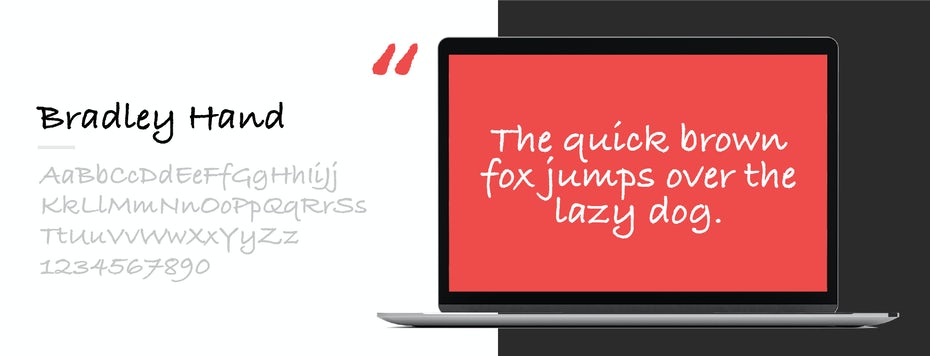
Шрифт Bradley Hand
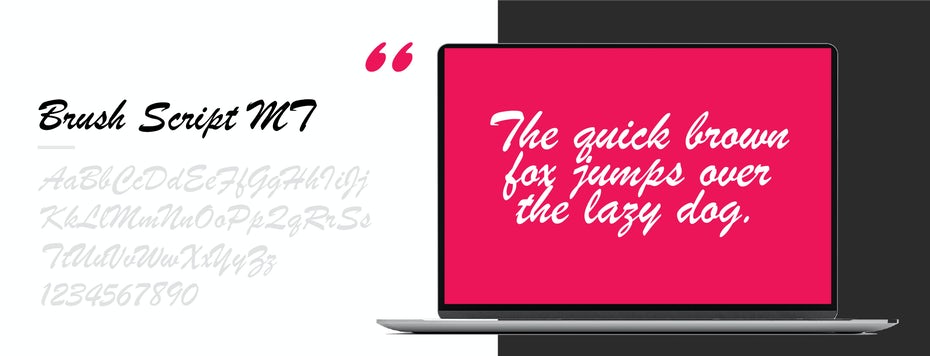
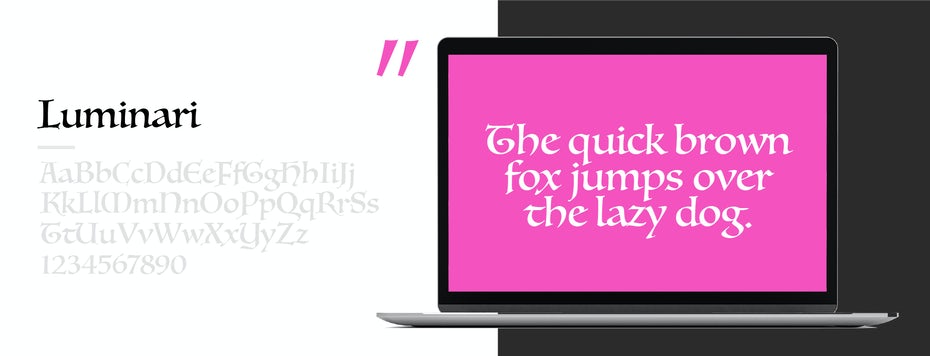
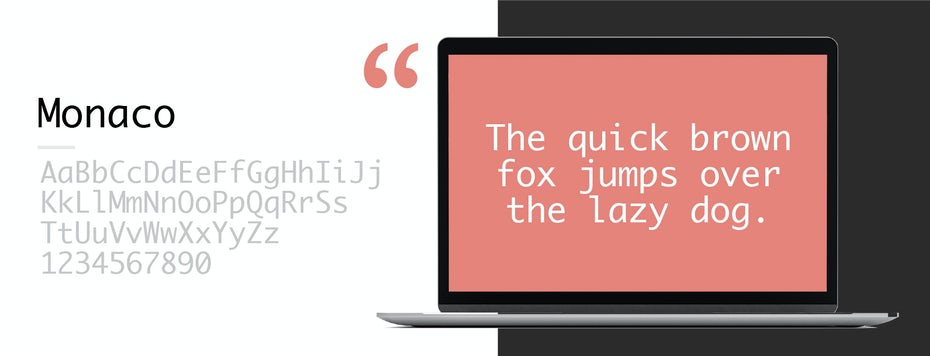
Или вы можете просто использовать Comic Sans.
Выбор веб-шрифта для вашего сайта – важное решение, которое влияет как на то, как посетители используют ваш сайт, так и на то, как они воспринимают ваш бренд. Чтобы быть уникальным и завоевать авторитет в своем веб-дизайне, часто нужно найти лучший веб-шрифт, а не лучший веб-шрифт. Применение правильного шрифта в правильных местах влияет на то, какие элементы будут видны в первую очередь, а при стратегическом использовании может увеличить конверсию, время пребывания на сайте и многие другие бизнес-цели.
Если это решение кажется слишком сложным, вы всегда можете просто использовать Comic Sans. В конце концов, какая вам польза от смертных, если вы можете ходить среди богов?